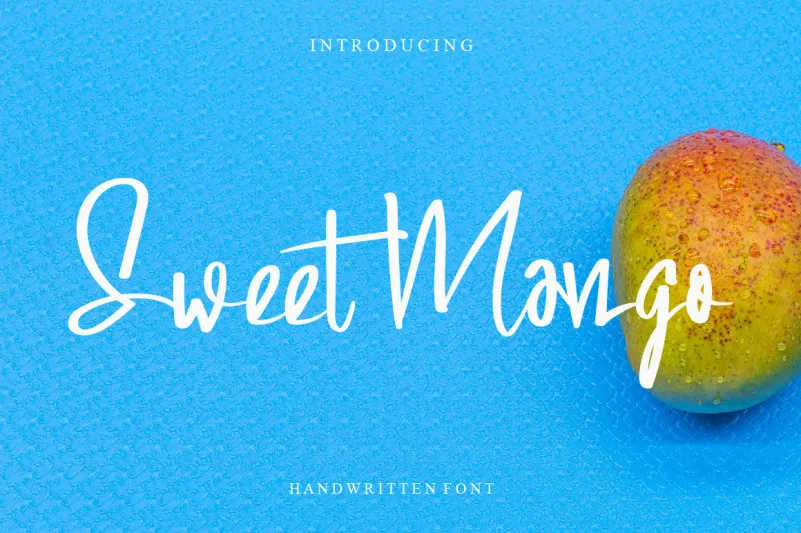
Sweet Mango Font – Fonte Grátis
Sweet Mango Font
A ‘Sweet Mango Font’ é uma elegante fónta feita para designers que procuram um toque leve e delicado em seus projetos. Esta fónta cursiva e escrita a mão, com seu traço fino e delicado, se encaixa perfeitamente em designs variados. Ideal para adicionar um tom de felicidade e romantismo a qualquer projeto. Ela é uma escolha ideal para designers que desejam imprimir ao design algo suave, comovente e levemente açucarado. A ‘Sweet Mango Font’ está disponível no estilo handwritten para designers em busca de uma fónta perfeita para adicionar um toque único a seus trabalhos. Seja você uma marca digital ou designer gráfico que busca incorporar o bom gosto ao seu design, esta fonte é ideal para incluir nos seus projetos.